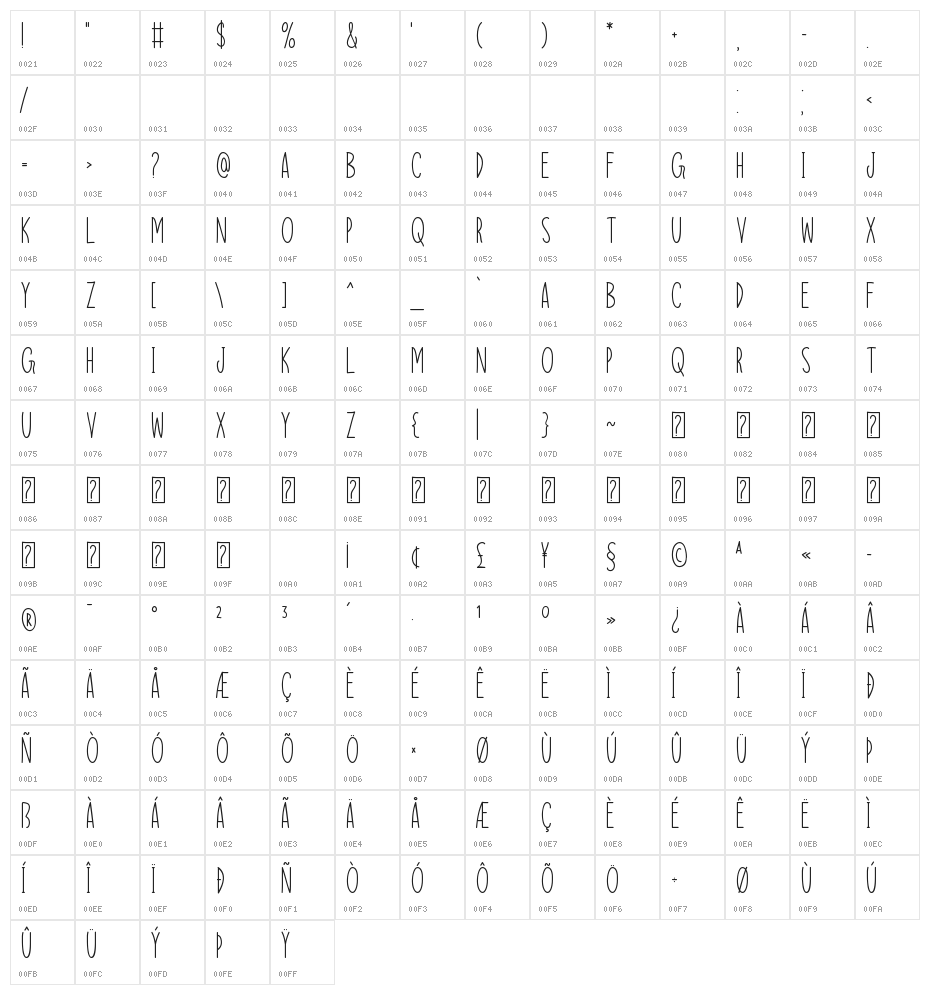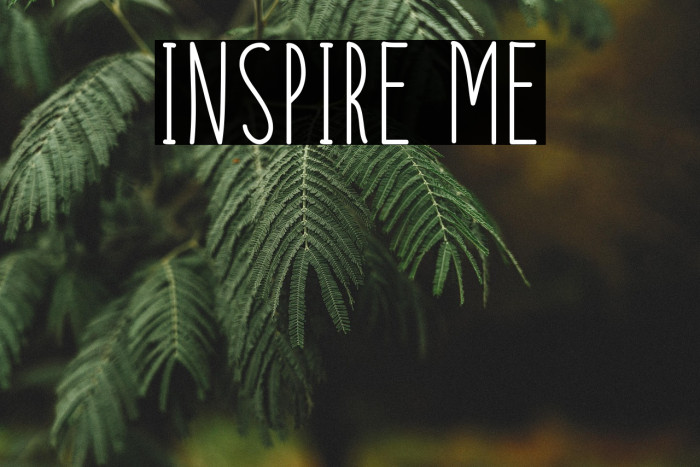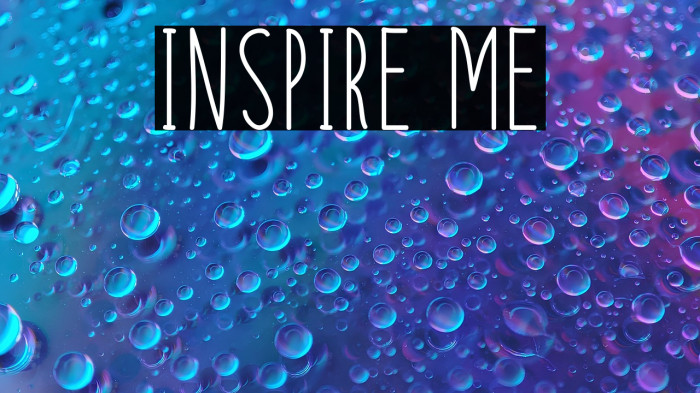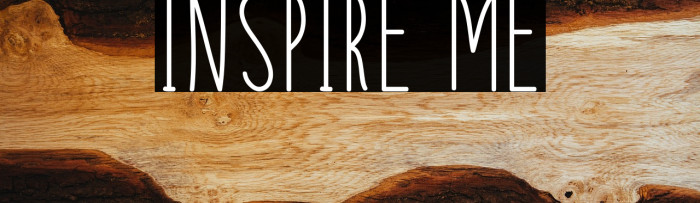
Inspire Me Font
| Gesamtstil | Playful |
| Anwendungsfall | Headlines, Logos, Creative projects |
| Vorgeschlagene Projekte | Ideal for greeting cards, children's books, playful branding, and creative posters. |